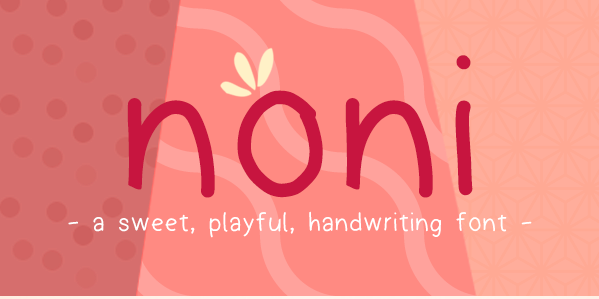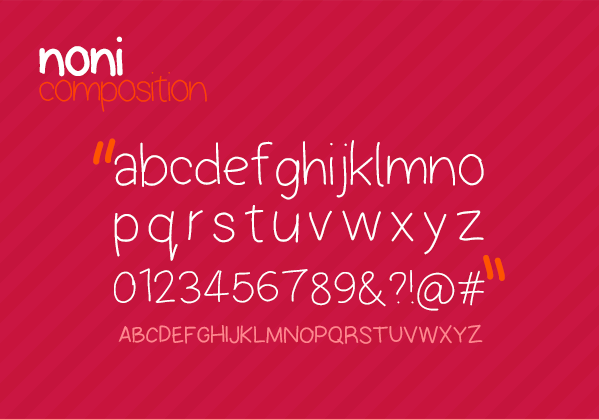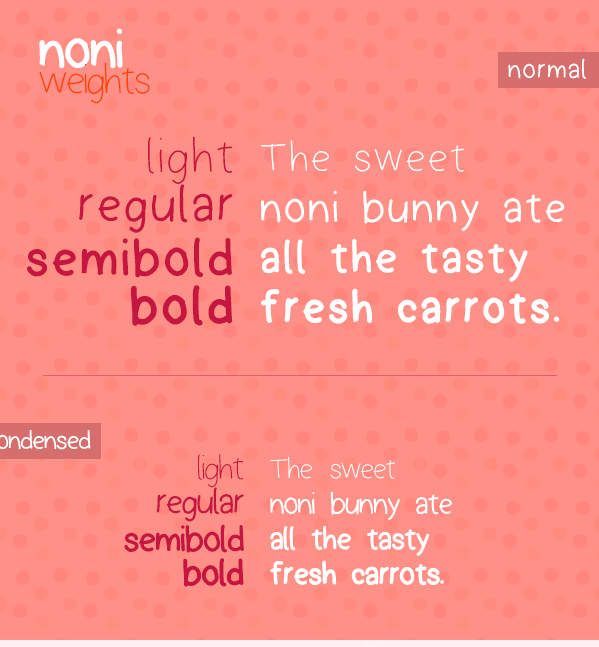
La tipografía de hoy es noni, una fuente creada mano sin reglas ni medidas. Su creador, el egipcio Ahmed Barakat, cuenta que la creó usando la pantalla de su teléfono móvil y la convirtió usando instafont. Esperamos que os guste.